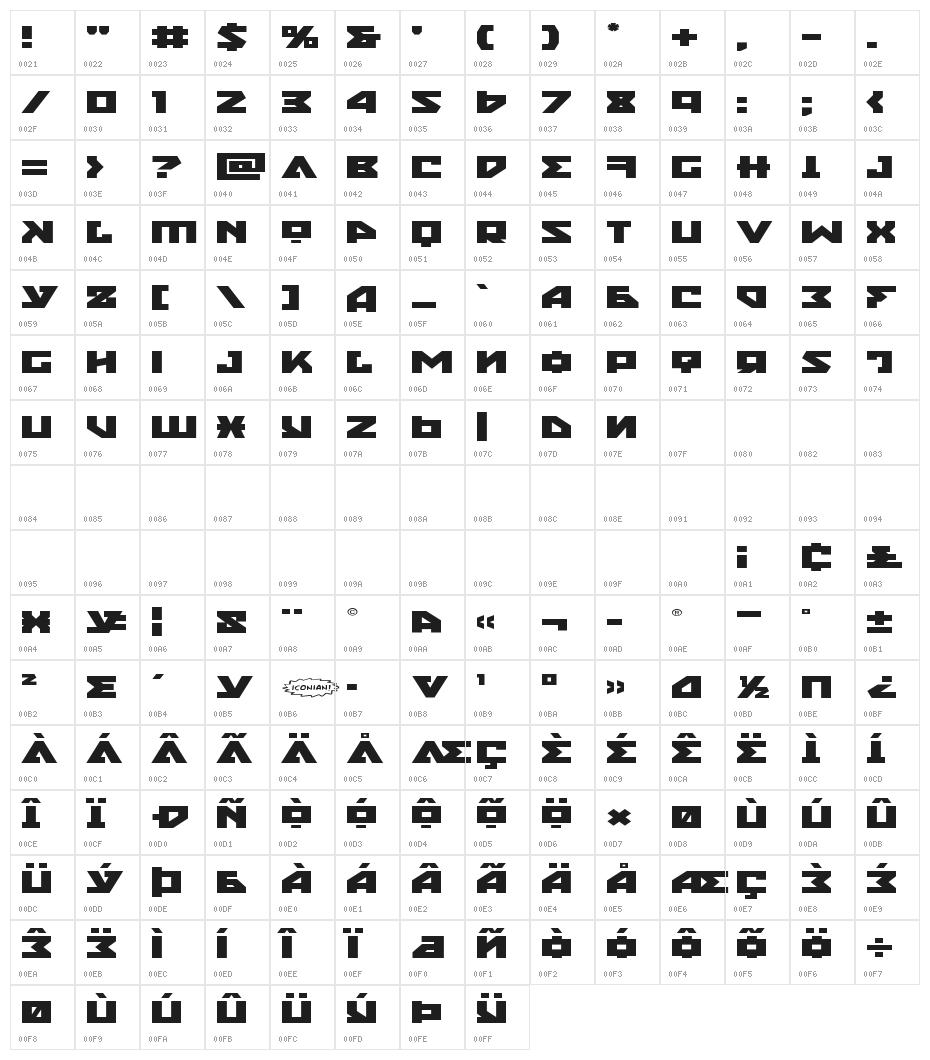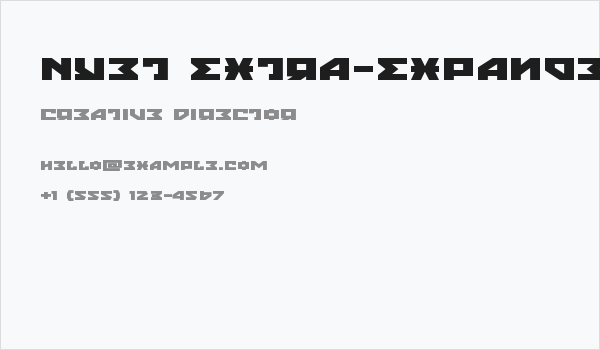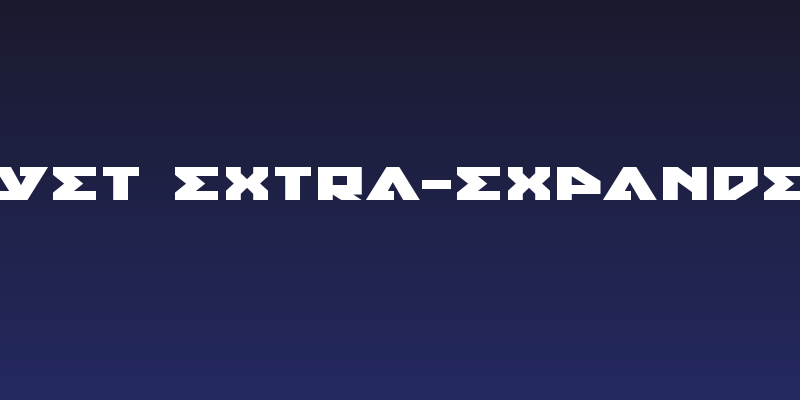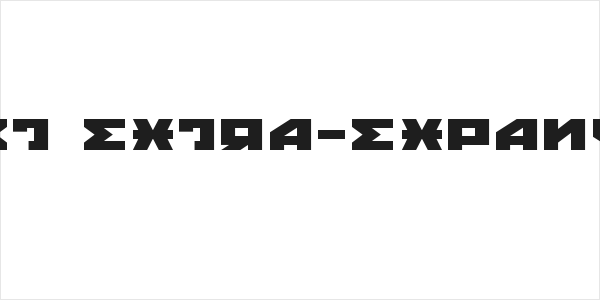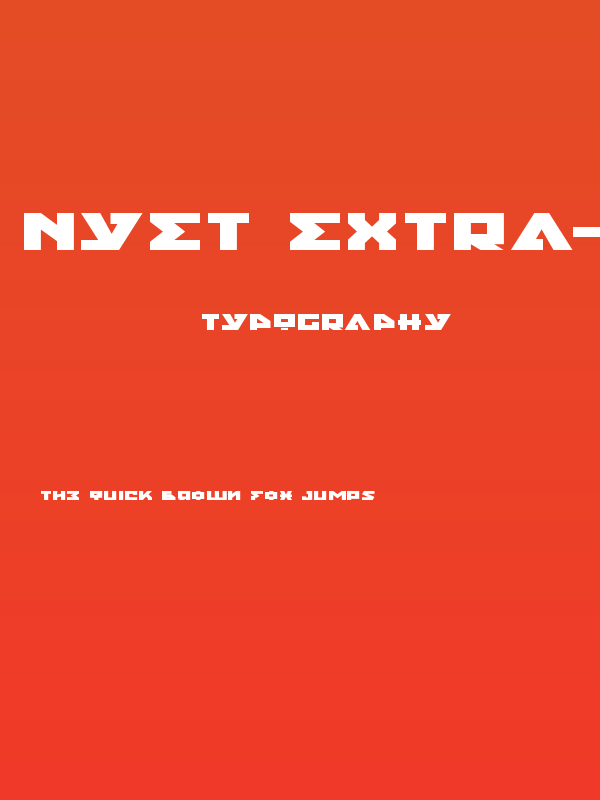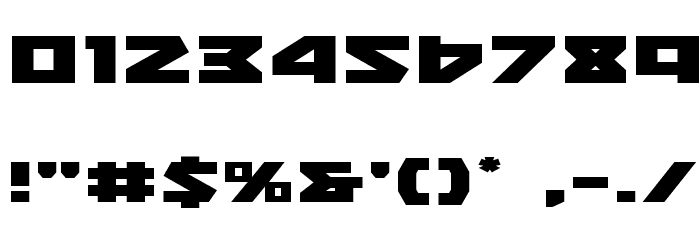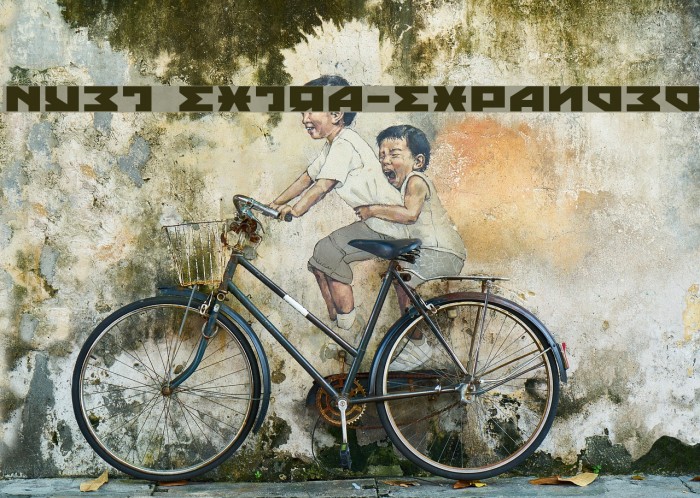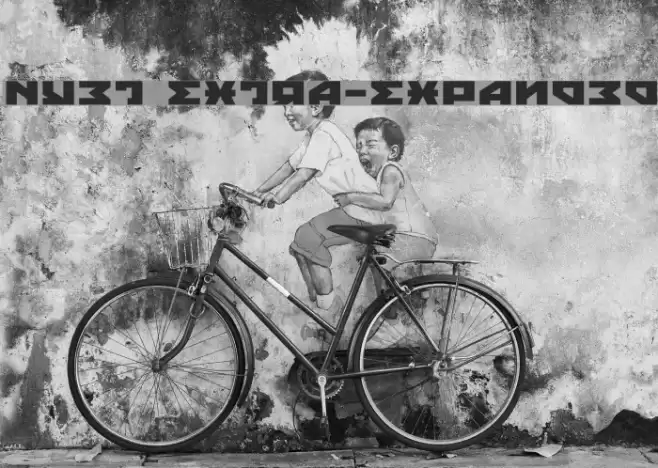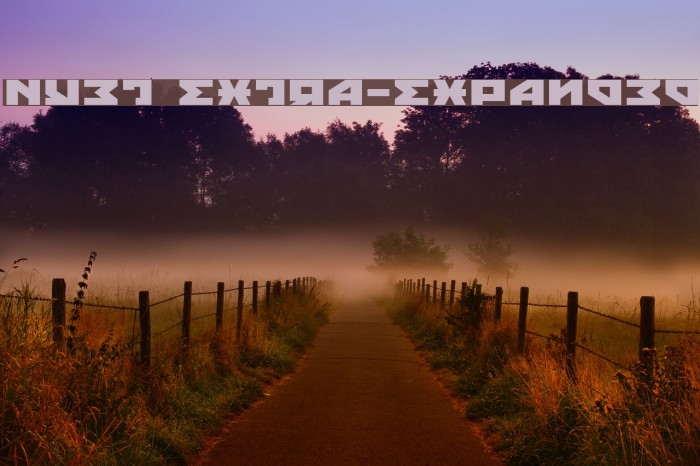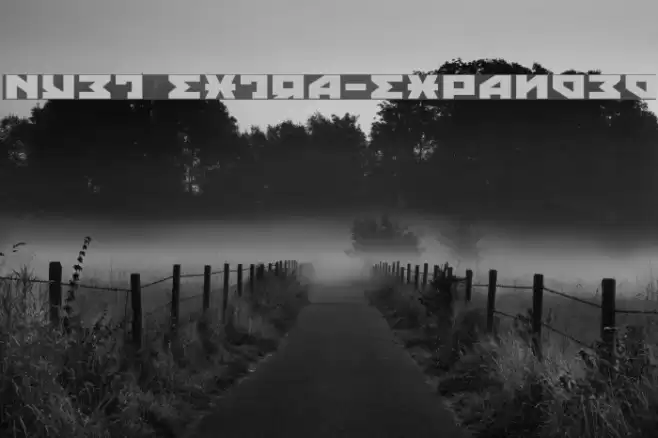
Nyet Extra-Expanded Font
| おすすめプロジェクト | Ideal for sci-fi themed posters, video game titles, branding for tech companies, and modern art installations. |